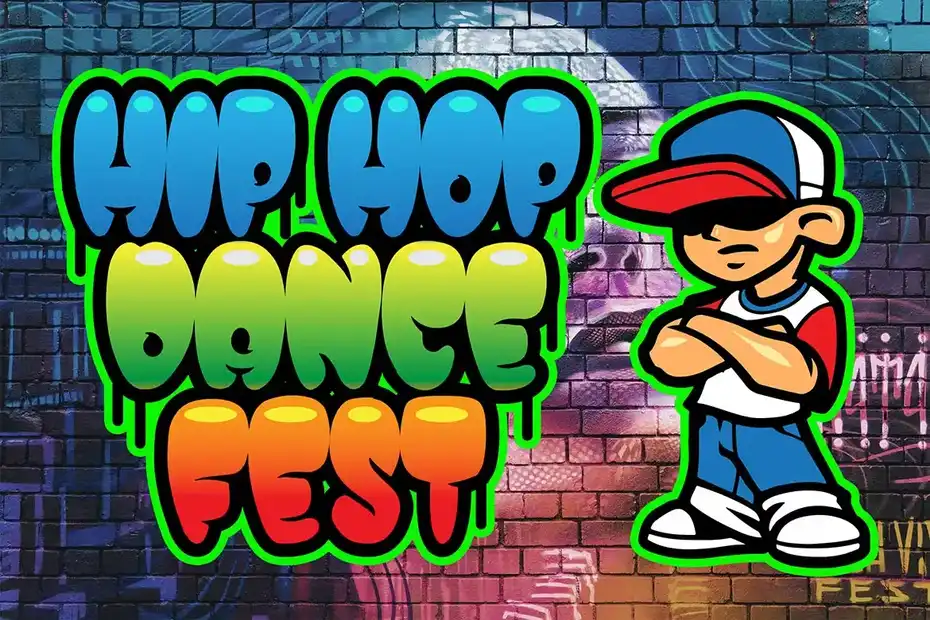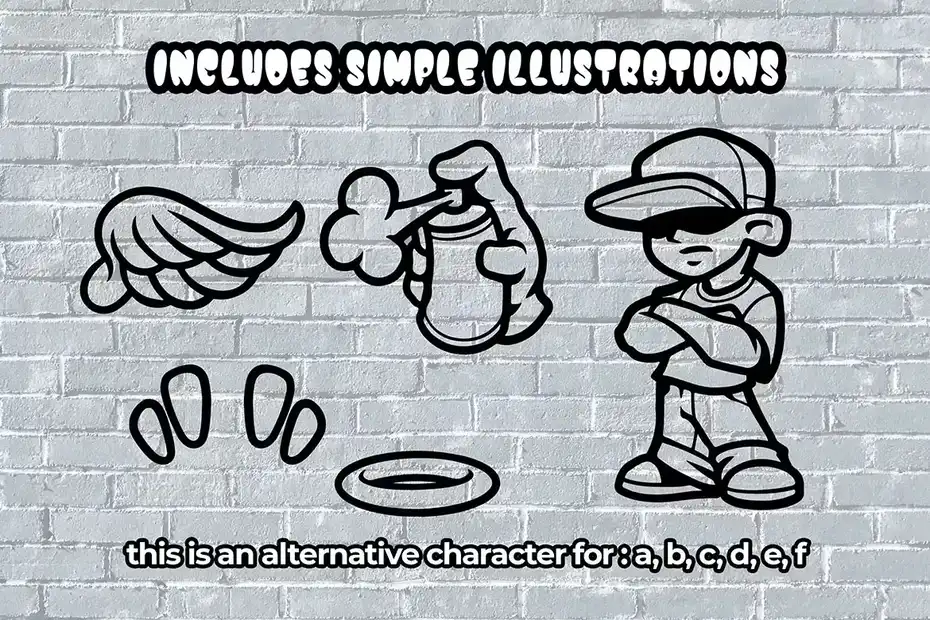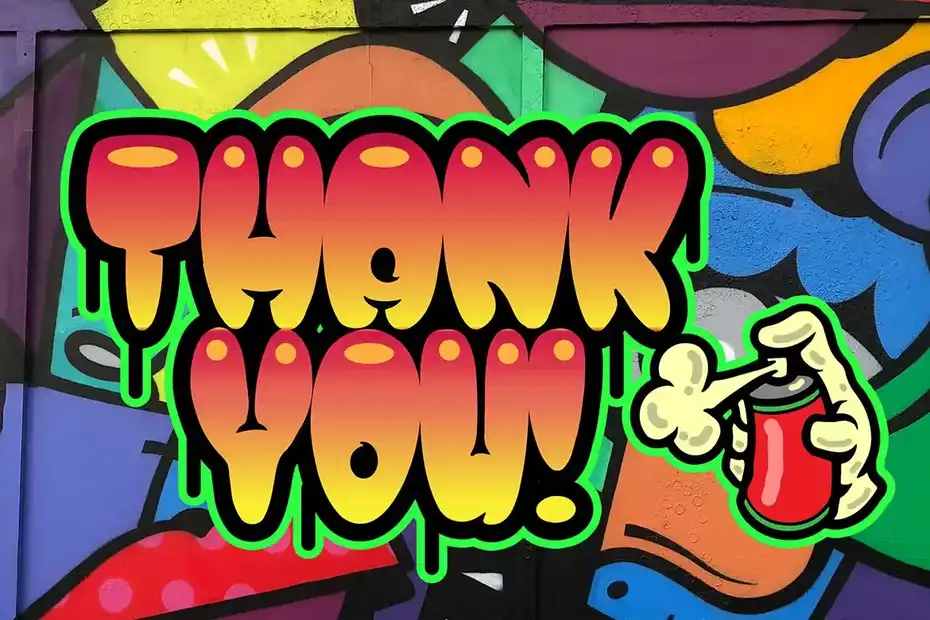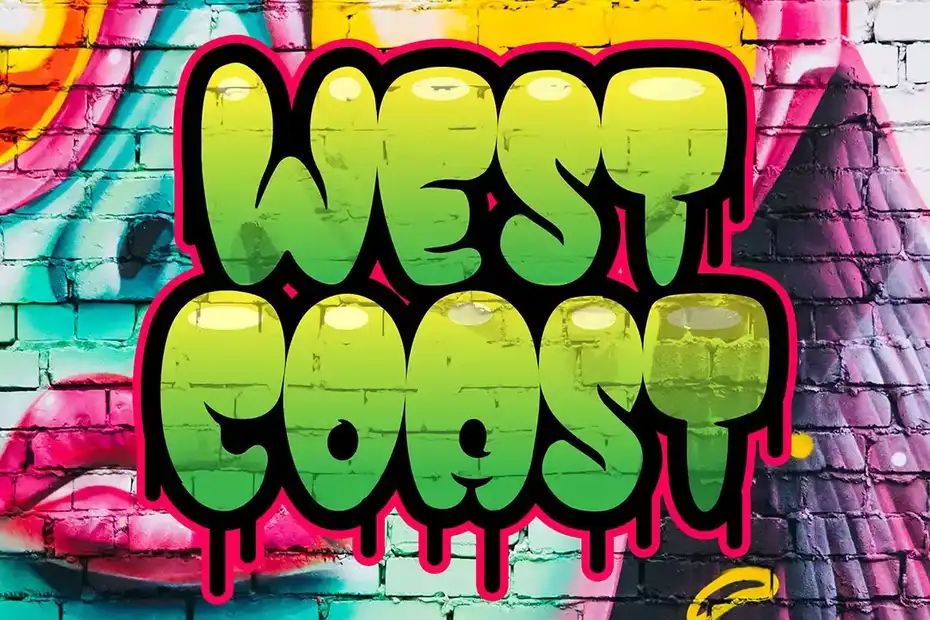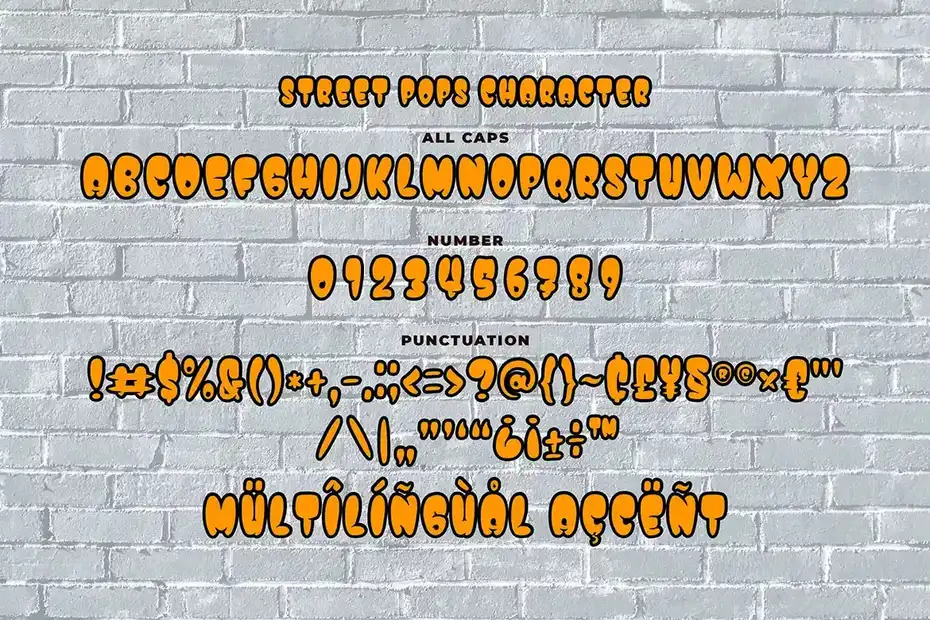
دانلود فونت گرافیتی کارتونی Street Pops – Graffiti Typeface
دانلود فونت گرافیتی کارتونی : این مجموعه شامل یک فونت انگلیسی گرافیتی کارتونی است که برای پوستر گرافیتی، موسیقی هیپ هاپ، پوستر کودکان، بروشور، کتاب کودکان، کارتون، کمیک و غیره مناسب میباشد.
• عنوان مجموعه: Street Pops – Graffiti Typeface